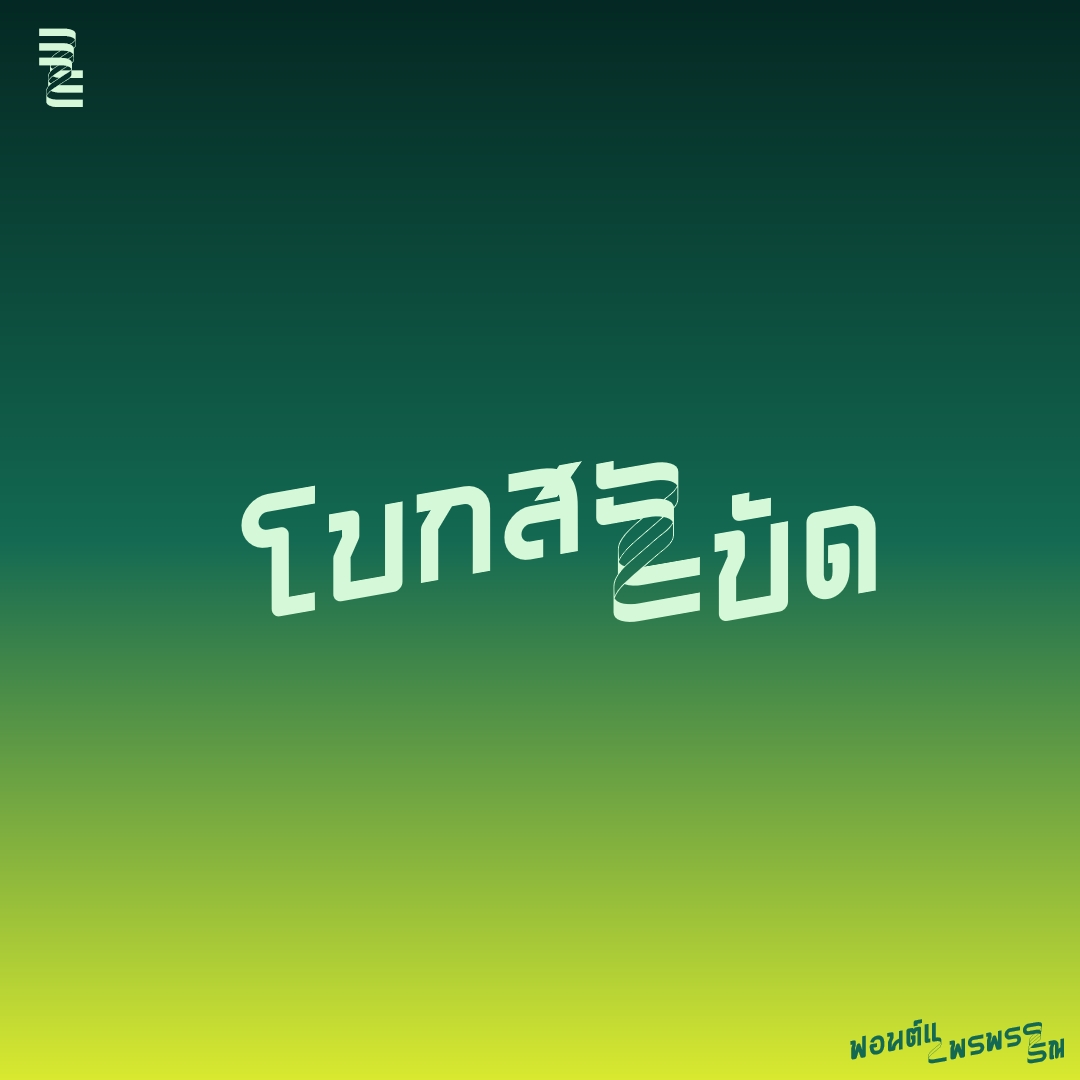
ฟอนต์ แพรพรรณ
ฟอนต์แพรพรรณ เป็นฟอนต์ริบบิ้นอีกแบบหนึ่ง อาจเรียกว่าเป็นธง เป็นผืนผ้า น่าจะเหมาะกว่า ใช้เป็น logo font ..แต่จะใช้กับประโยคก็ได้ ยังไงก็สะดุดรอยพับอยู่แล้ว
คำแนะนำ: ถ้ายังไม่ถูกใจ ให้เคาะ space หน้าอักษรตัวแรก จนกว่าจะพอใจ ..กด bold เพิ่มลูกเล่นรอยพับ